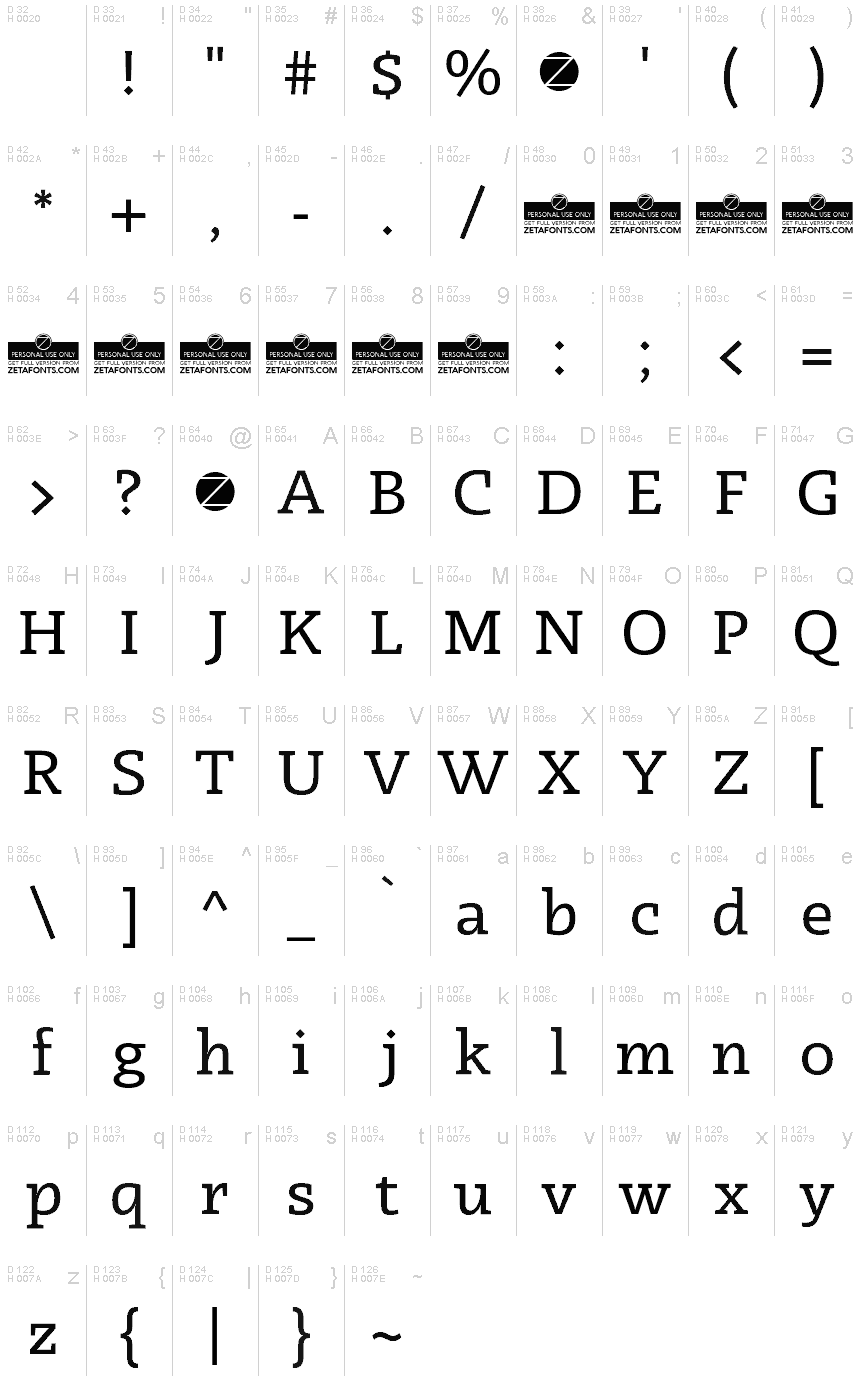
Radcliffe هي عائلة خطوط صممها كوزيمو لورينزو بانشيني وأندريا تارتاريلي في عام 2018، كإعادة ابتكار لتصميم Clarendon التقليدي بحثاً عن مظهر «كلاسيكي معاصر». صُمم خط Radcliffe ليعكس الأناقة، ويتميز بزوايا قوية ذات تباين منخفض، ومحور عمودي، وهو ما يشتهر به خط Clarendon، ولكنه صُقل بلمسة إنسانية ومنهج خطي يظهر بوضوح في الأنماط المائلة.
صُمم Radcliffe في المقام الأول كخط للعناوين مع مجموعة واسعة من الأوزان المضبوطة بدقة لأغراض التحرير وتصميم الشعارات، ويكمله خط Radcliffe Text، الذي طورناه بخمسة أوزان مع ارتفاع أكبر لأحرف x ونسب أكثر تكثيفاً قليلاً، مما يسمح بأقصى قدر من القراءة في النصوص الطويلة على الويب وبأحجام صغيرة.
تتضمن العائلة أيضاً وزنين مميزين لخط Radcliffe Casual، صُمما بجمالية التباين المعكوس، مما يجعلهما مثاليين لأنشطتك في النادي الريفي (Country Club). تتضمن جميع خطوط Radcliffe ميزات OpenType كاملة مع بدائل أسلوبية، ووصلات اختيارية (ligatures)، وأشكال أرقام موضعية، وأشكال مزخرفة (في الخطوط المائلة)، ودعم لغوي كامل لأكثر من 70 لغة تستخدم الأبجديات اللاتينية والسيريلية.
Radcliffe Display